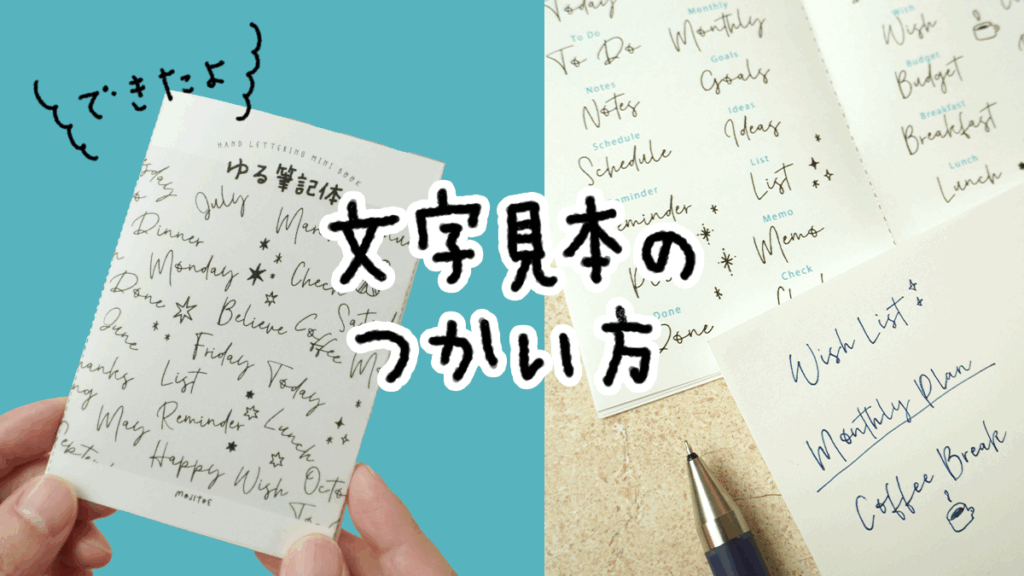
おしゃれなゆる筆記体♪文字見本の使い方
手帳やノートをちょっとおしゃれにしたいときに役立つのが「筆記体の文字見本」。A〜Zのアルファベットや数字、記号、曜日や月名などがまとまっていると、どこからでも気軽に真似して書けます。今回は、そんな文字見本の使い方やアレン … 続きを読む おしゃれなゆる筆記体♪文字見本の使い方